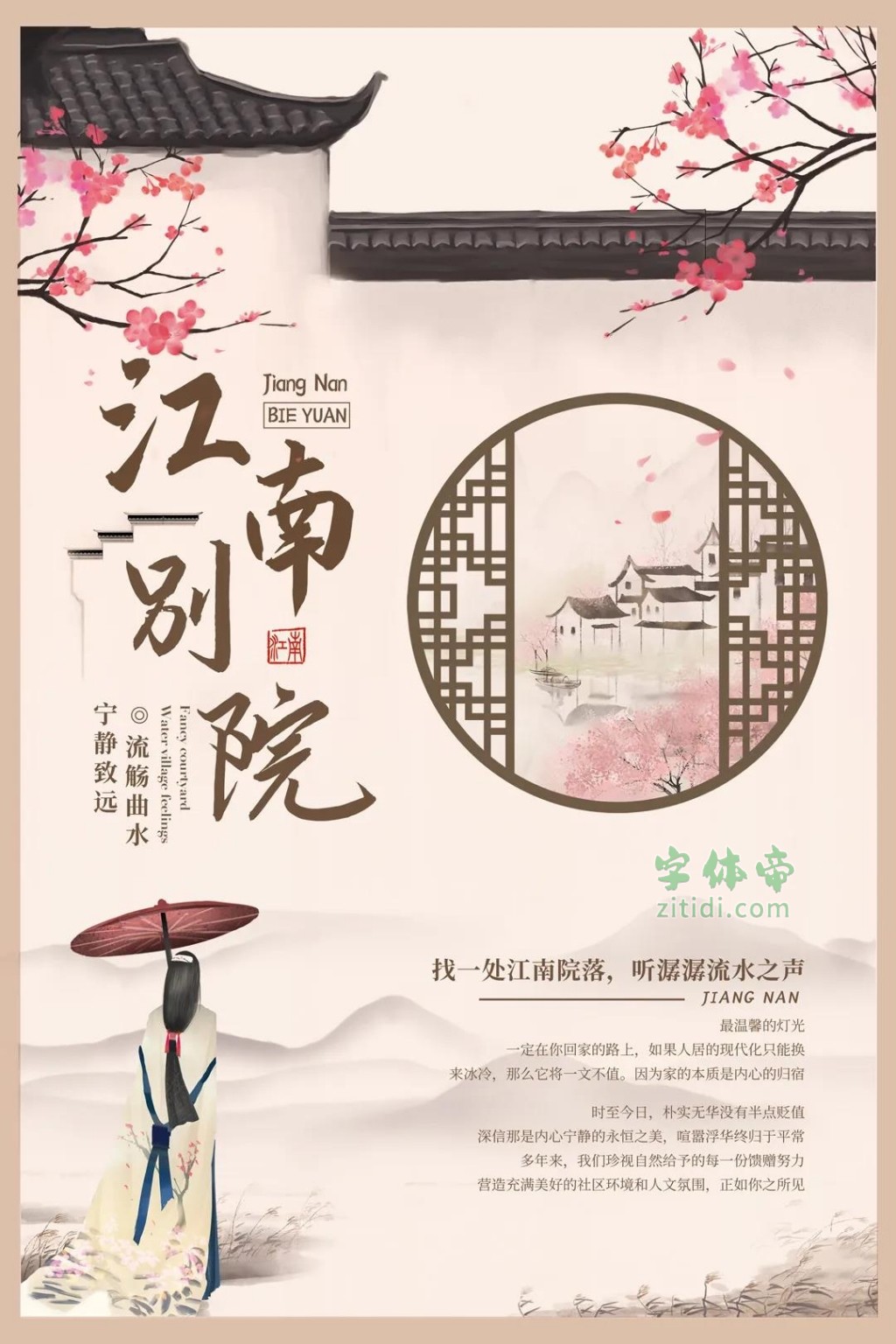
《辞海》有语:形体方正,笔画平直,可作楷模。说的,便是楷书 楷体中以小楷清秀流丽、润泽含蓄,可填补系列字的中庸之位,于是便有了这款演示悠然小楷。
初看演示悠然小楷,可能并不觉得惊艳,再品,却会发现透着质朴、率真的气息。正如尚在象牙塔中的作者本人,那是未经雕琢的拙朴书生气。
接下来,我们一起体会悠然小楷的这股拙气。
1、关于字形
悠然小楷笔画分明,结构清晰,没有过度的连笔和飞白,对阅读识别更为友好;
小楷字形较小,天然拥有更大的字间距,即便作为长段文字使用,阅读上也不会有太大视觉压力;
2、关于笔形
悠然小楷的笔画力度分布均衡,起收有序,没有太过强烈的对比,自然沉劲而不漂浮;
在小楷的基础上有些行楷的影子,为字体增添了灵动,但又有克制,形成停而不断、笔断意连之态;
部分笔画细节可能并不完美,不够顺滑,但这份未经雕琢,又何尝不是一种难得的拙朴;
关于字体作者
都说“字如其人”,你猜,写出这套字的是怎样的一个人? 字稿的作者,是一位很漂亮的女孩,这款演示悠然小楷的字稿作者——孟祥媛,生于1999年,是一位目前还在大学就读的书法专业的学子。
“演示悠然小楷2.0”是一款书写很新颖的字体,字体大方,适合各种设计作品使用!欢迎下载!